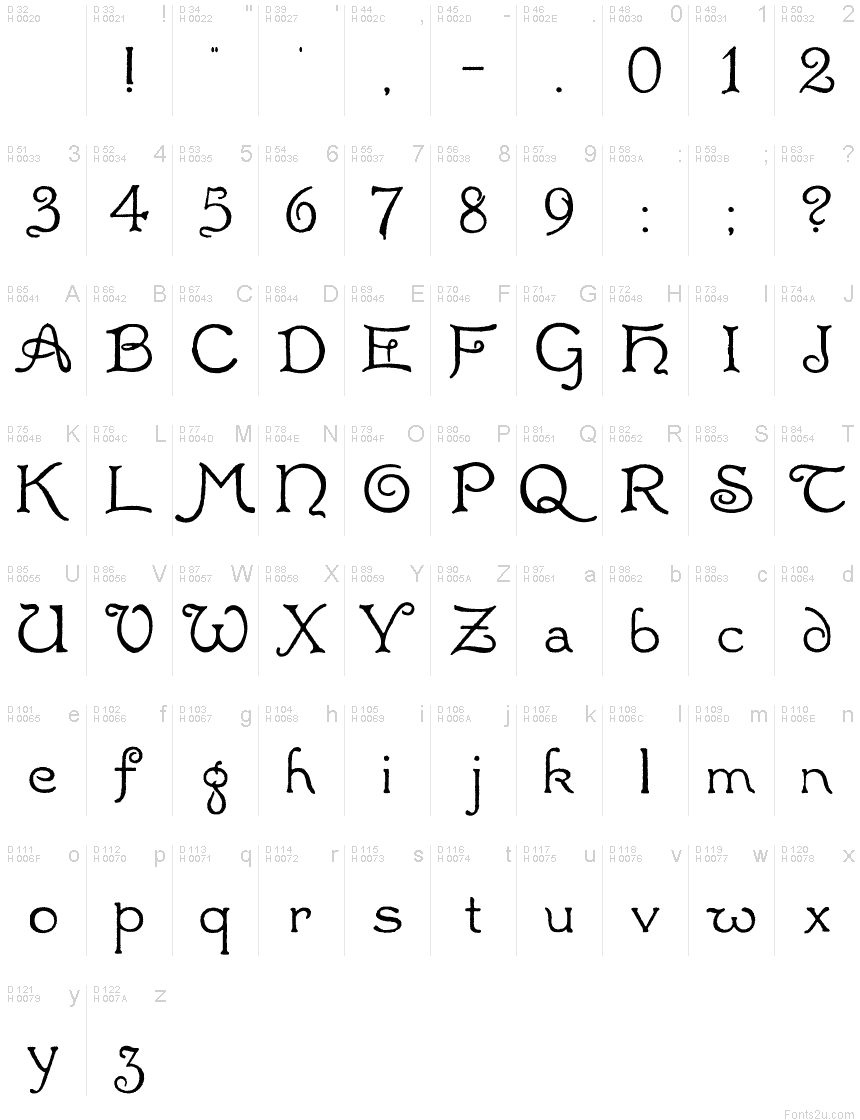
Radaern, di PJL, è un font display gratuito e ricco di riccioli, con un'atmosfera da libro di fiabe e un tocco leggermente medievale. Le lettere mescolano forme con grazie morbide, tratti lunghi e avvolgenti e curve irregolari; il risultato è un carattere dall'aspetto artigianale, un po' ribelle, tutt'altro che formale o ordinato.
È perfetto per copertine di libri, branding di caffetterie, poster, volantini di eventi e packaging che richiedono un tocco letterario o folkloristico. Essendo un font gratuito, è ideale per titoli brevi, targhette e monogrammi, poiché quei tratti alti e sinuosi danno carattere anche a poche lettere.